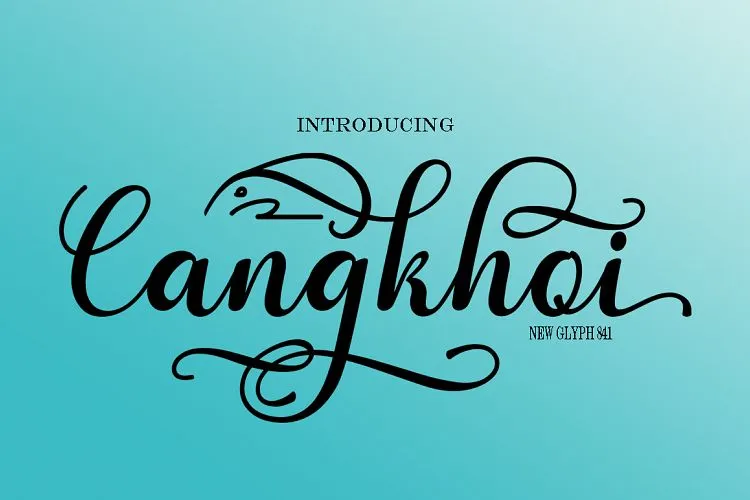
Cangkhoi Script Font – Fonte Grátis
Cangkhoi Script Font
Introduzimos a Cangkhoi Font. Desenvolvida com estilo fresco e moderno combinando elementos de letra à mão, caracteres decorativos e linhagem animada, essa fonte oferece uma proposta de design que se destaca para aplicativos como cartas de convite, cartões de lembrança, material de marca, cartões de negócios, citações, panfletos e muito mais. Cangkhoi é perfeita para estilos requintados e elegantes, mas também possui um toque jovem e inovador que a torna versátil para diversas necessidades de design. Seja para criar cartões de aniversário personalizados ou materiais de marca para sua empresa, a Cangkhoi oferece uma solução com o desenho único que você merece.